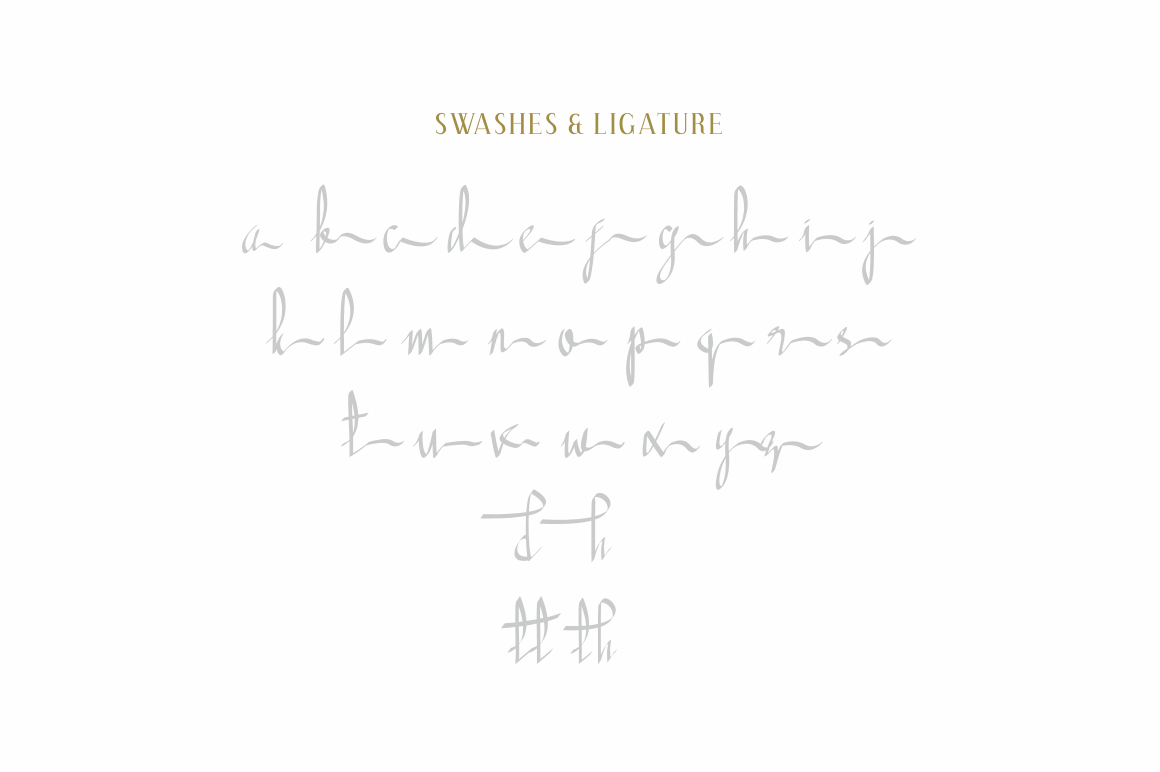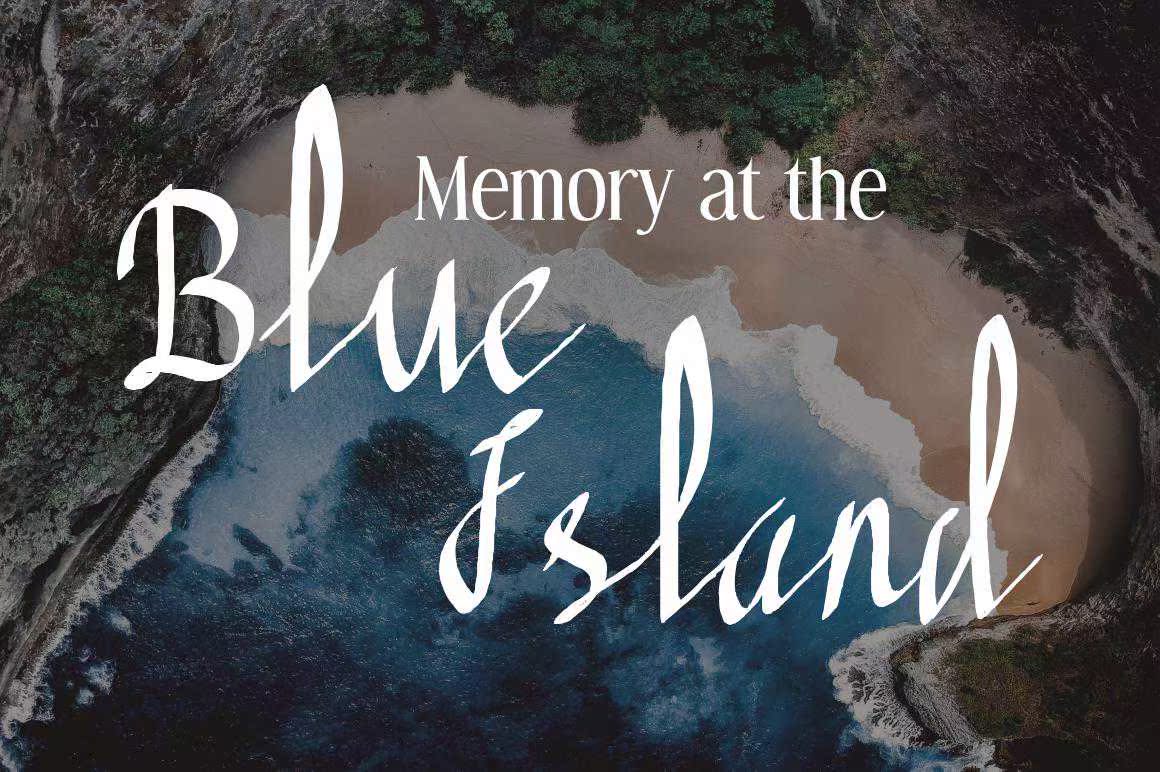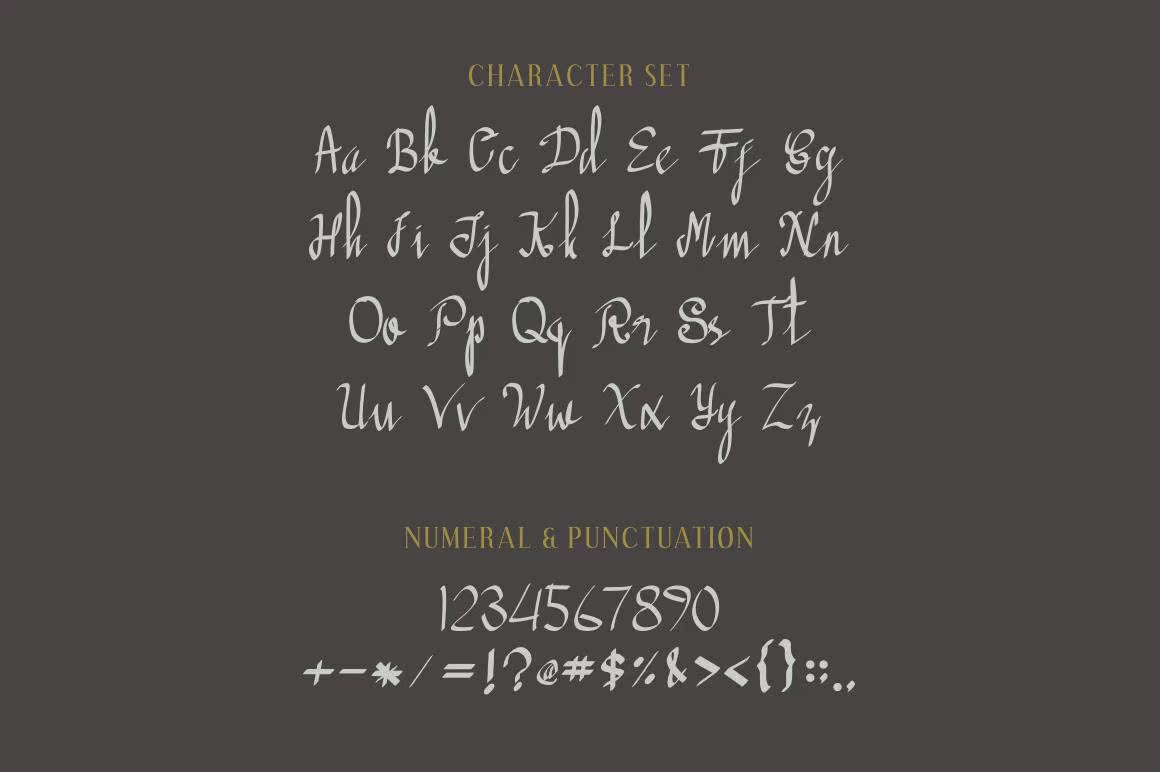
Glianchais适用于需要标题、标识、服装、邀请、品牌、包装、广告的用户。我们创建了DitInPiredByTenature,Glianchameis来自Glyph和Bianca,这是一种白色字形。Glianchais适用于需要标题、标识、服装、邀请、品牌、包装、广告的用户。我们创建了DitInPiredByTenature,和Glianchanameis来自Glyphandbianca,它是一种白色的雕文。